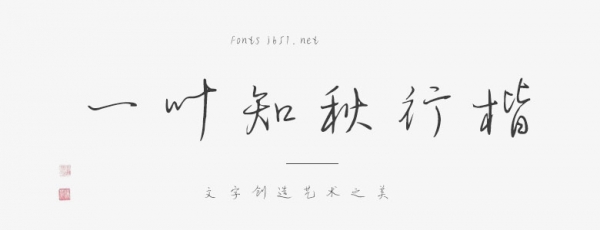
一葉知秋行楷這款字體的筆法剛硬,整體結(jié)構(gòu)左傾,筆鋒與連筆表現(xiàn)出書(shū)寫(xiě)意趣,是一款具有高識(shí)別性的實(shí)用手寫(xiě)體,能夠有效增加畫(huà)面的意境感。適用于現(xiàn)代詩(shī)歌、短文的排版,以及文化、商業(yè)類品牌的廣告語(yǔ)設(shè)計(jì)。